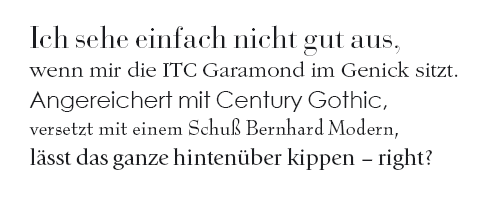
Mischungsmonster
ich benötige eine Abstrusitätensammlung von Schriften, die niemals, also wirklich unter keinen Umständen gemischt werden dürfen! Also etwas echt Abstoßendes, schauderhaft-widerlich-grauenerregend, eben einfach geschmacklos muss es sein!
Hat hier jemand entsprechende Killerkombinationen auf Lager?
Wirklich absolut geschmacklos willst du?
Arial + Times New Roman, bei gleicher nominaler Punktgröße
(und als Sahnehäubchen in Word ohne Kerning gesetzt, aber das war ja nicht die Frage).
eigentlich gibt es unzählige beispiele, worauf willst du hinaus?
helvetica und futura würde ich nicht mischen
oder garamond und times usw.
das hier geht auch gaaaar nicht:
... bei den Klassizistischen Antiquas ist es recht deutlich: die Schlechtmischung Bodoni--Minion hatte ich bereits auf der schwarzen Liste.
Einen Egyptienne-Tanker mit einer Renaissance-Antiqua-Brigg kollidieren zu lassen... ja, das ist auch gemein! ;)
Rotis & Rotis sans
Futura & Avantgarde
News & Gill
Bodoni & Syntax
Alles auf dem Weg zur Arbeit gesehen. :-)